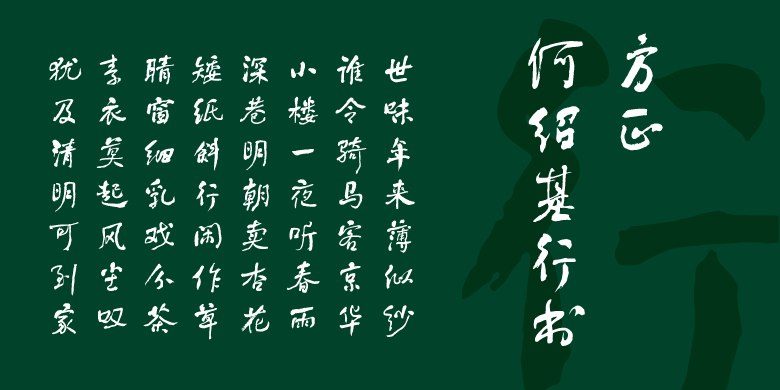
方正何绍基行书
• 整理/设计:
苏新诗,杨龙龙
行书、常规书写·毛笔
关于何绍基:
何绍基(1799-1873年),晚清书法家兼诗人,字子贞,号东洲居士,晚号蝯叟,湖南道州人。官至文渊校理,武英殿篆修、学政等职。曾主讲于长沙城南书院、寓长高码头东洲草堂。他精通金石书画,以书法著称于世。
字体特征:
方正何绍基行书是基于何绍基行书《论画》的风格特点开发的;字体洒落自然、挺秀沉雄。
整理/设计:苏新诗,杨龙龙